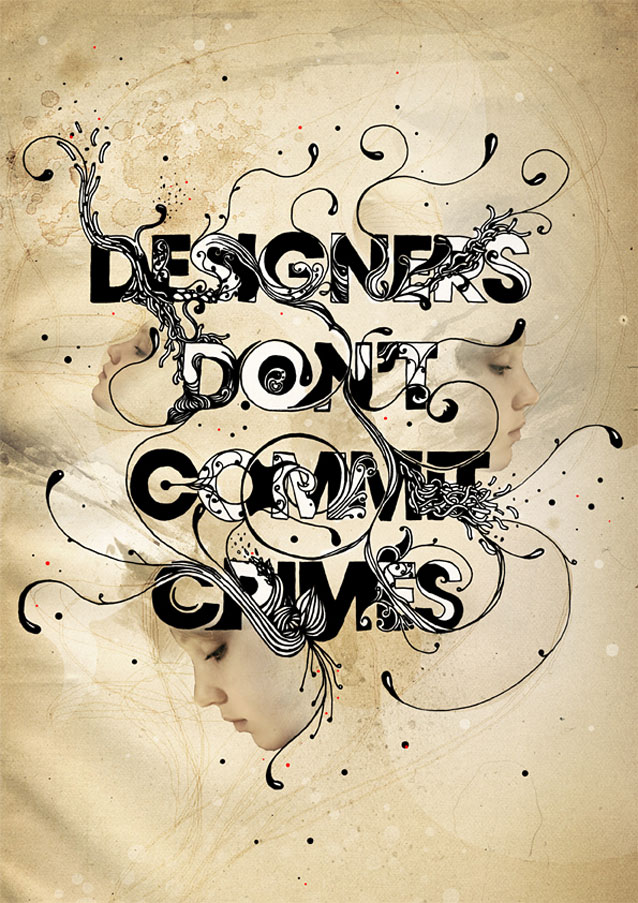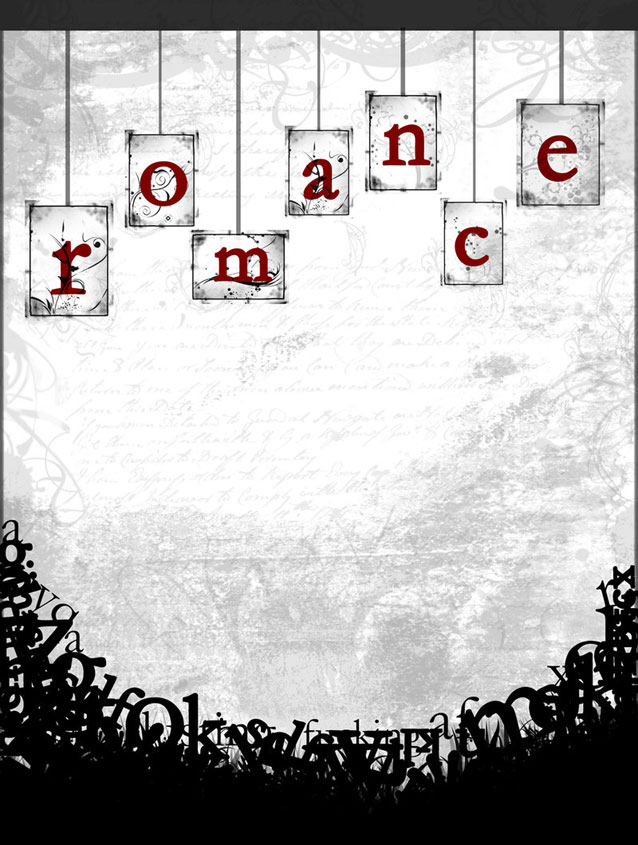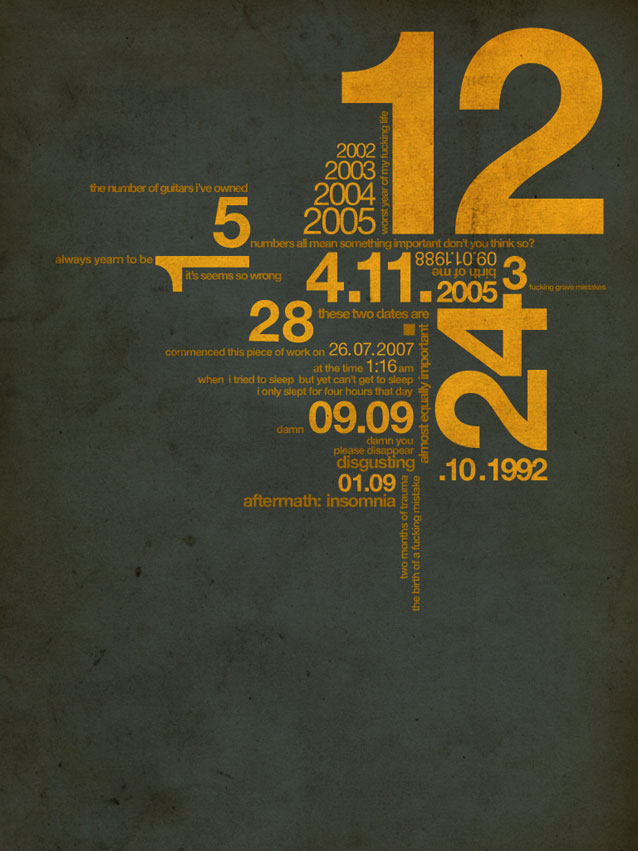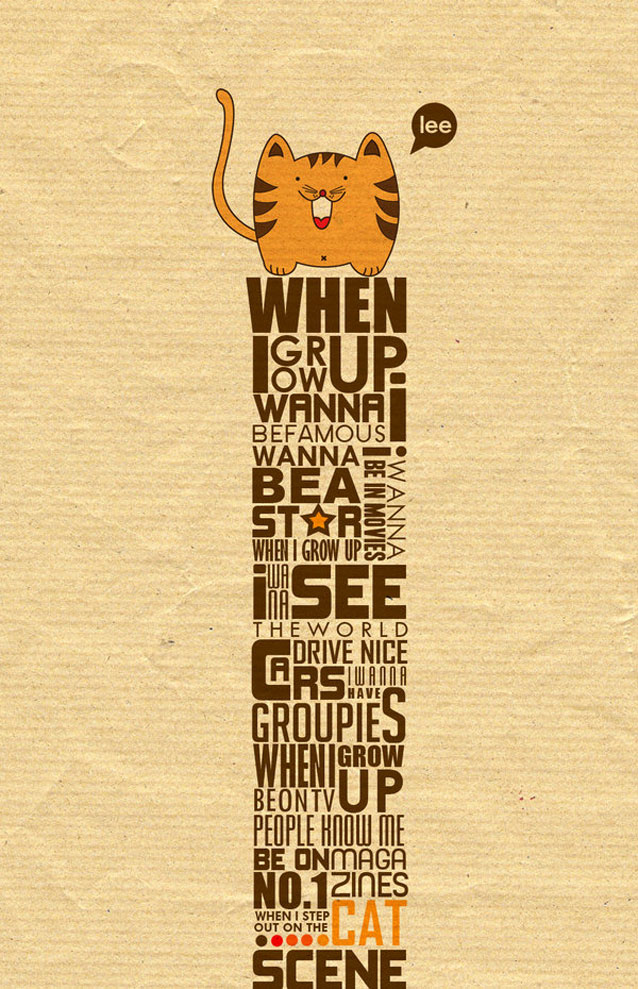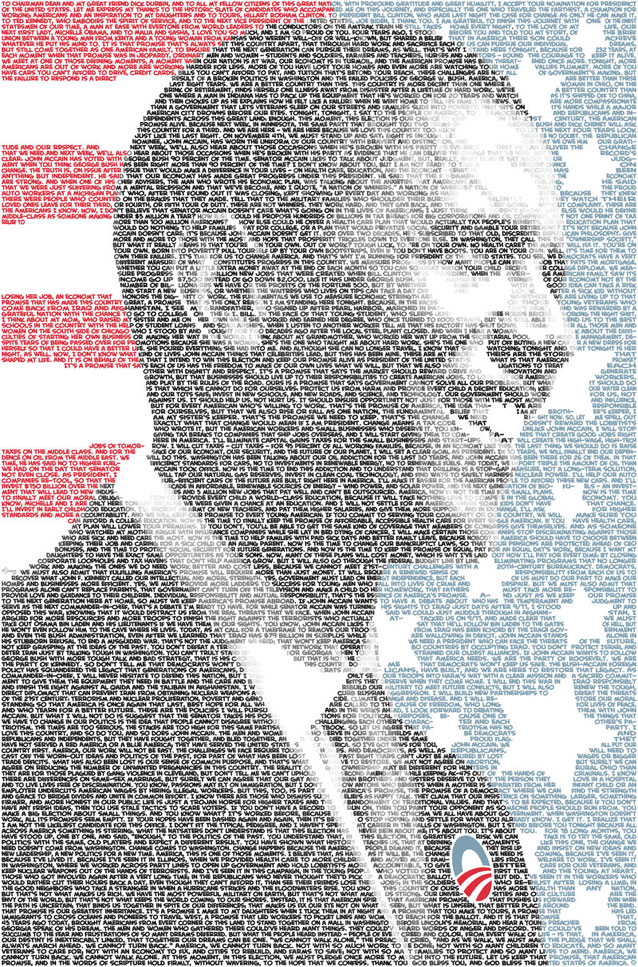
Este post tiene como origen a cssbuilt donde han hecho una selección de diseños a base de tipografÃas, a que me refiero? bueno en un diseño de poster no es necesario utilizar fotografÃas o gráficos llamativos basta con utilizar palabras con las cuales se pueden formar objetos u ordenándolas adecuadamente se le puede dar un toque original y único a nuestro diseño.
He aquà algunos de los diseños artÃsticos con base de tipografÃas, si alguien conoce el nombre de este estilo de diseños comentelo, compartamos conocimiento.
Que les pareció estos excelentes diseños artÃsticos? si quieren conocer los otros solo sigan el siguiente enlace.
Excelentes carteles. Me considero un gran admirador de este tipo de carteles tipográficos (que te parece ese nombre?
)